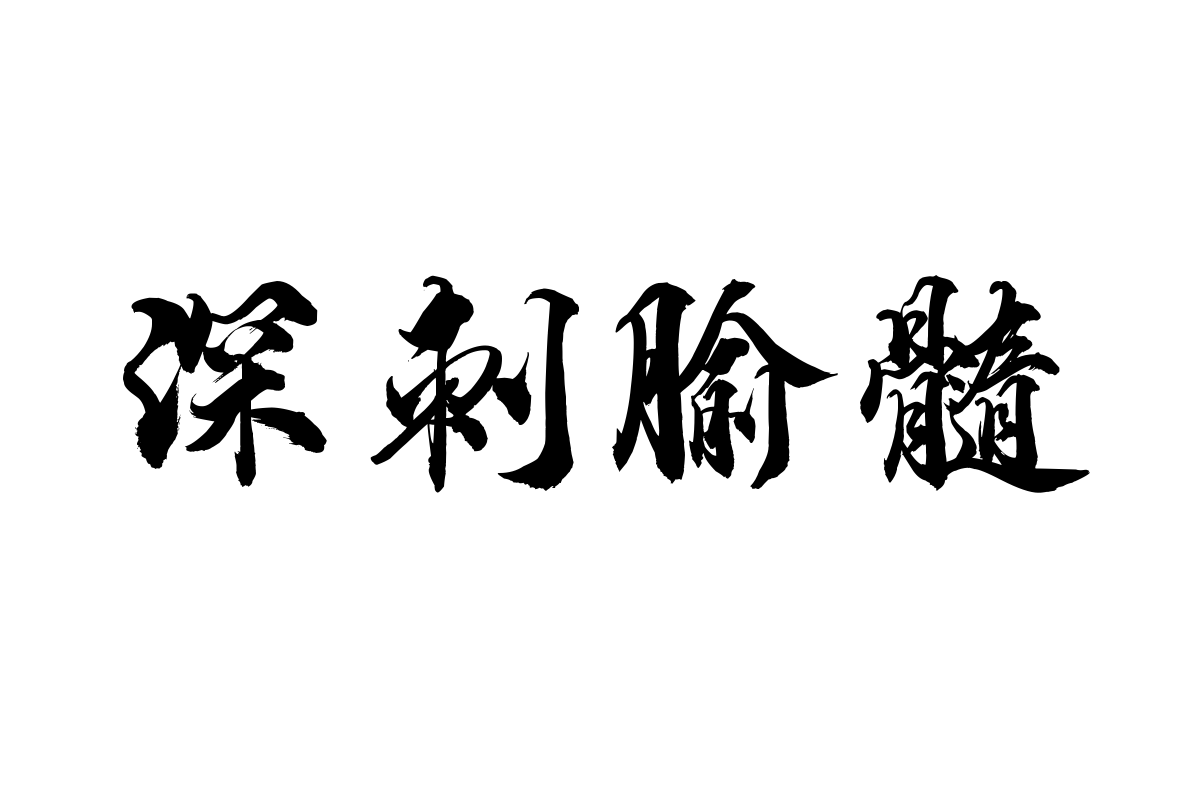
段宁毛笔行艺体是一种具有独特风格的书法字体,它的特点是线条流畅,结构紧凑,笔画饱满,给人一种古朴而优雅的感觉。这种字体在书写时需要有一定的功底和技巧,才能展现出其独特的魅力。
段宁毛笔行艺体的字形结构严谨,笔画粗细有度,既有力度又不失柔和。它的线条变化多端,既有直线的刚劲,又有曲线的柔美,给人以美的享受。此外,段宁毛笔行艺体的字形大小不一,既有大字的豪放,又有小字的精致,使得整个字体充满了变化和层次感。
总的来说,段宁毛笔行艺体是一种具有很高艺术价值的书法字体,它不仅能够展现书写者的才华和修养,还能够给人带来一种宁静、和谐的审美体验。